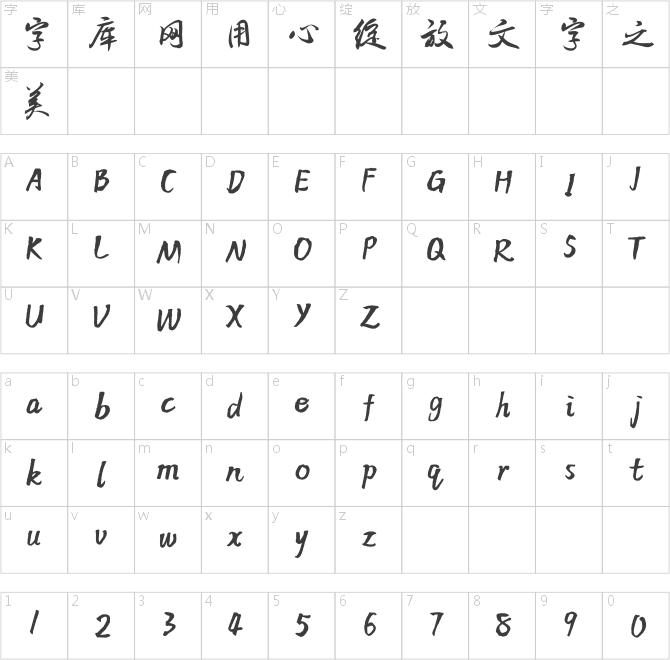
方正字跡-逸龍快書 詳情頁
逸龍快書,逸龍書體系列之一。顧名思義,快書介于行書和草書之間,以書寫快速而名。偏于草書但字形盡量保持行書識別標準,方便現代非專業人士認知和識別,注重實用功能。快書承襲逸龍體既有的飄逸灑脫,行云流水,矯若游龍。兼有二王灑逸之風,顏筋柳骨之格,蘇放黃剛之韻,還有趙秀啟雅之美。融百家之美,成一家之奇。收放自如,追求自然,實為當代新風清流之書體。 作者劉龍斌,廣東興寧人,跨界職業設計師,書法家。愛好廣泛,尤其對中國傳統文化藝術有著深厚的情感。對中國的書畫詩詞都頗為愛好,在鉆研學習書法過程中,取長補短,不拘一格。